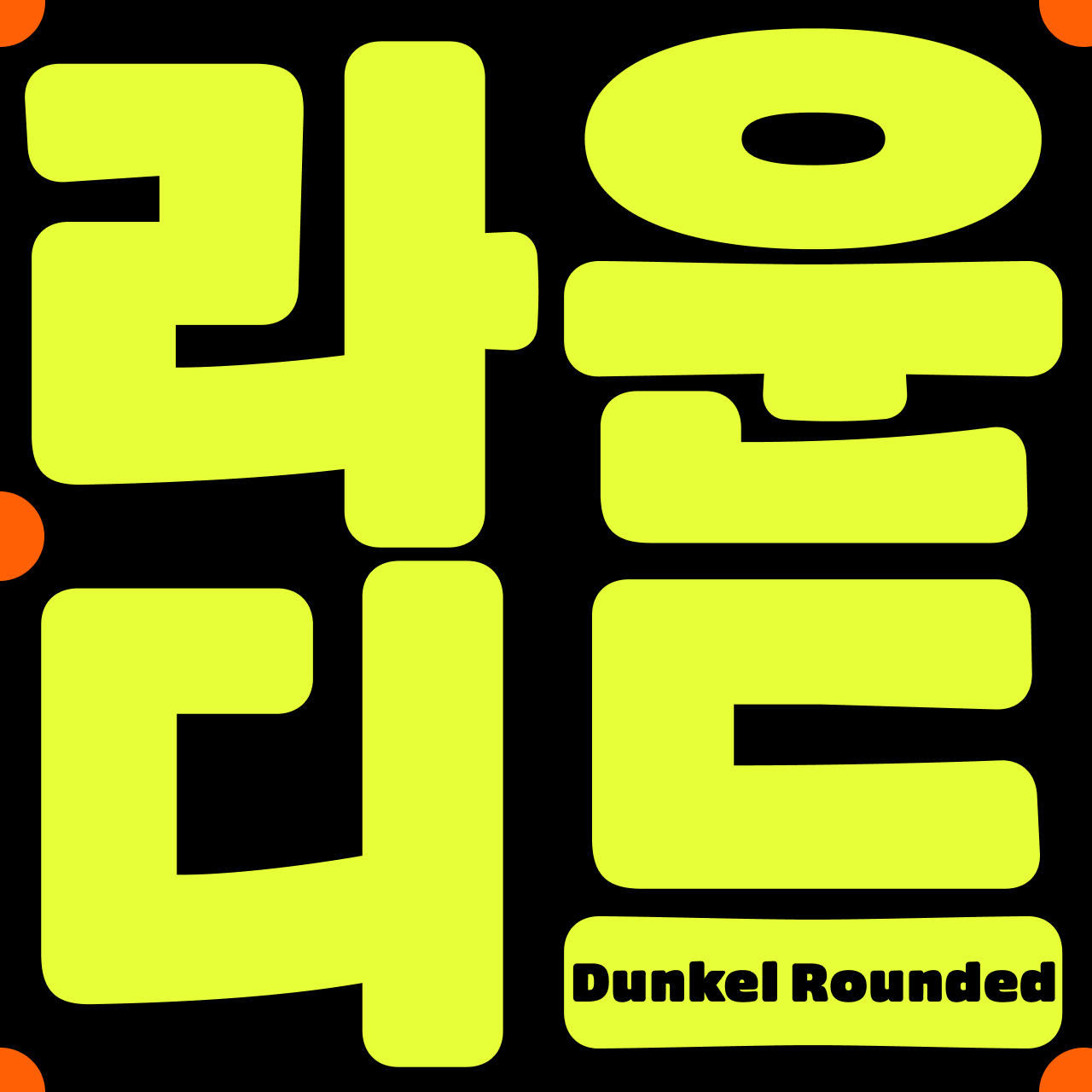
둥켈산스의 라운디드 버전을 소개합니다.
획의 모서리를 둥글게 굴려 부드럽고 따뜻한 이미지를 갖고 있습니다.
둥켈산스 라운디드 Condensed Rounded Condensed Rounded
둥켈산스 라운디드 Expanded Rounded Expanded Rounded
둥켈산스 라운디드 Round Black Round Black
둥켈산스 라운디드 SemiCondensed Rounded SemiCondensed Rounded